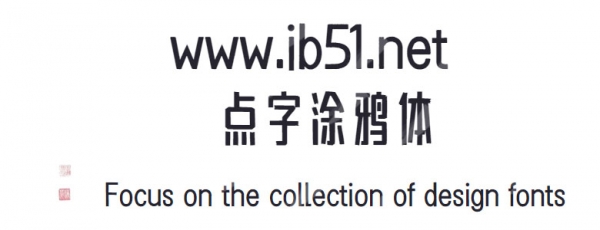
點(diǎn)字涂鴉體是由點(diǎn)字庫推出的藝術(shù)字體,字體字形瘦長,結(jié)構(gòu)勻稱,筆畫起收筆帶有板刷紋理,適合應(yīng)用于藝術(shù)設(shè)計(jì)、各類廣告和產(chǎn)品包裝設(shè)計(jì)等領(lǐng)域。
字形瘦長,結(jié)構(gòu)勻稱。筆畫起收筆帶有板刷紋理,氣質(zhì)俊秀活潑,更具視覺表現(xiàn)力。